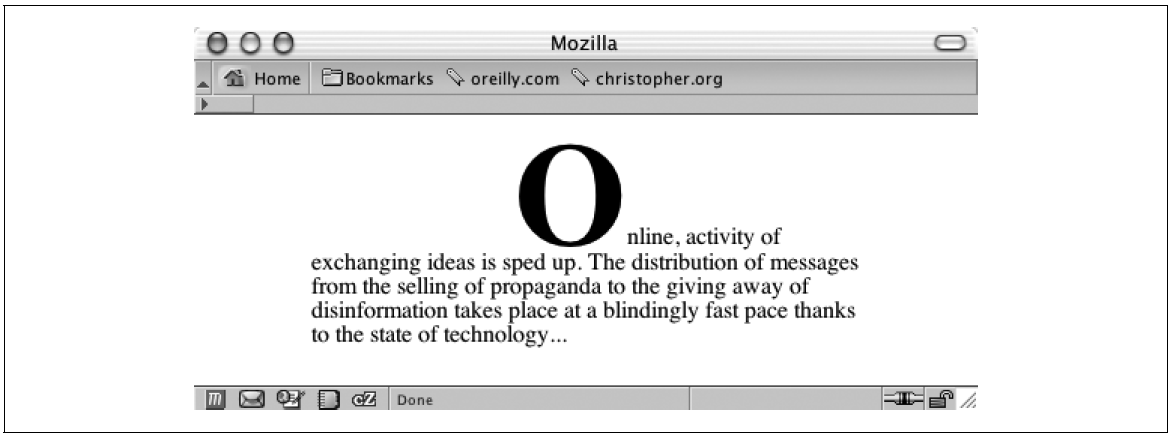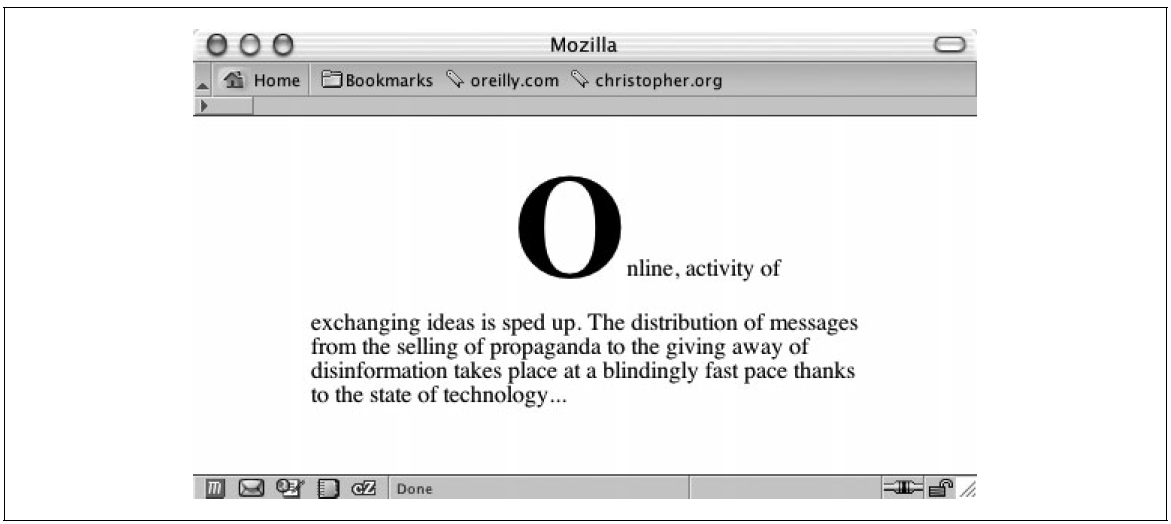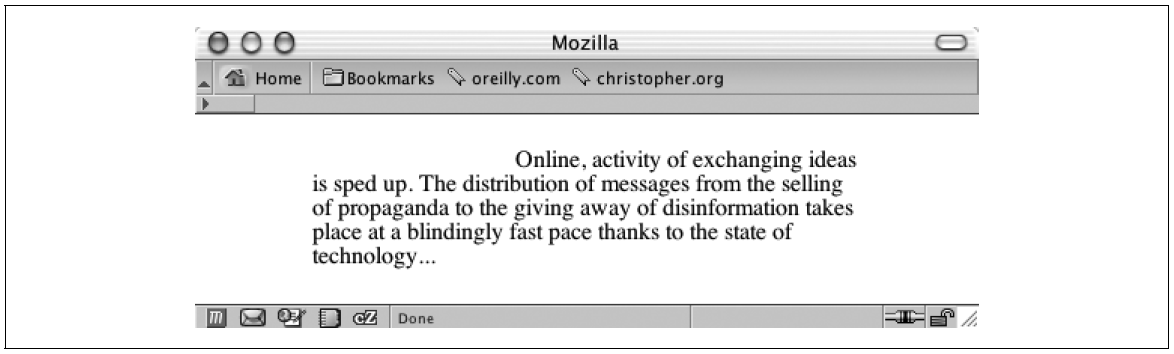
Größere und zentrierte Versalien
Problem
Ein großer Versal soll in der Absatzmitte platziert werden.
Lösung
Umgeben Sie den ersten Buchstaben des ersten Satzes des Absatzes mit einem span-Element, das ein class-Attribut besitzt:
<p><span class="initcap">O</span>nline, activity of exchanging ideas is sped up. The distribution of messages from the selling of propaganda to the giving away of disinformation takes place at a blindingly fast pace thanks to the state of technology …</p>
Zusätzlich zu den Stildefinitionen für den ersten Buchstaben mit Hilfe des span-Tags und des Klassenselektors definieren Sie weitere Regeln, die die Einrückung für den Absatz festlegen (siehe folgende Abbildung):
p {
text-indent: 37%;
line-height: 1em;
}
p span.initcap {
font-size: 6em;
line-height: 0.7em;
font-weight: bold;
}
Abbildung: Ein größerer Versal, zentriert dargestellt.
Diskussion
Diese Lösung basiert auf dem Zusammenwirken dreier CSS-Eigenschaften. Die erste Eigenschaft ist text-indent, die die erste Zeile in Richtung Absatzmitte verschiebt. Der Wert wurde hier mit 37% angegeben. Das entspricht etwas mehr als einem Drittel der gesamten Breite (siehe die folgende Abbildung), ist aber nicht genug, um den Versal tatsächlich zu »zentrieren«.
Abbildung: Der eingerückte Text.
Die nächste Eigenschaft, die uns bei der Aufgabe hilft, ist font-size. Indem wir die Schriftgröße mit 6em angeben, legen wir fest, dass der Versal um das Sechsfache (bzw. 600%) größer als die Standardschriftgröße des Browsers dargestellt werden soll (siehe die folgende Abbildung).
Abbildung: Ein Versal, der sechsmal größer ist als die normale Schriftgröße.
Da die Schriftgröße sechsmal größer ist als der übrige Text, ist auch der Durchschuss der ersten Zeile höher als bei den übrigen Zeilen. Um das wieder zu korrigieren, stellen Sie die Zeilenhöhe für das span-Element auf 0.6em ein.
Die Zentrierung des Versals funktioniert in diesem Rezept, sofern die Breite des Zeichens 26% der Absatzbreite entspricht. Haben bei Ihnen der Versal oder der Absatz eine andere Breite als in diesem Rezept, müssen Sie gegebenenfalls die Werte in den CSS-Regeln anpassen, um den Versal zu zentrieren.